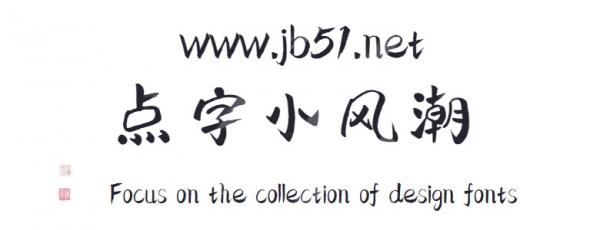
點字小風潮是由點字庫推出的藝術字體,字體筆觸適中,每個筆法的書寫均有一種“桀驁不馴”、“峰回路轉”的心理感受,看似“邪門歪道”,其實“有規(guī)可循”,適合應用于藝術設計、各類廣告和產品包裝設計等領域。
小風潮手寫體是對傳統(tǒng)軟筆書法方式的一次突破,每個筆法的書寫均有一種“桀驁不馴”、“峰回路轉”的心理感受,看似“邪門歪道”,其實“有規(guī)可循”。字于小處聽風賞潮,故為“小風潮”。該書體可適用于牌匾、包裝等實用場景,行業(yè)應用上如影視、游戲、動漫、電商、餐飲均有較好的視覺表現(xiàn)。